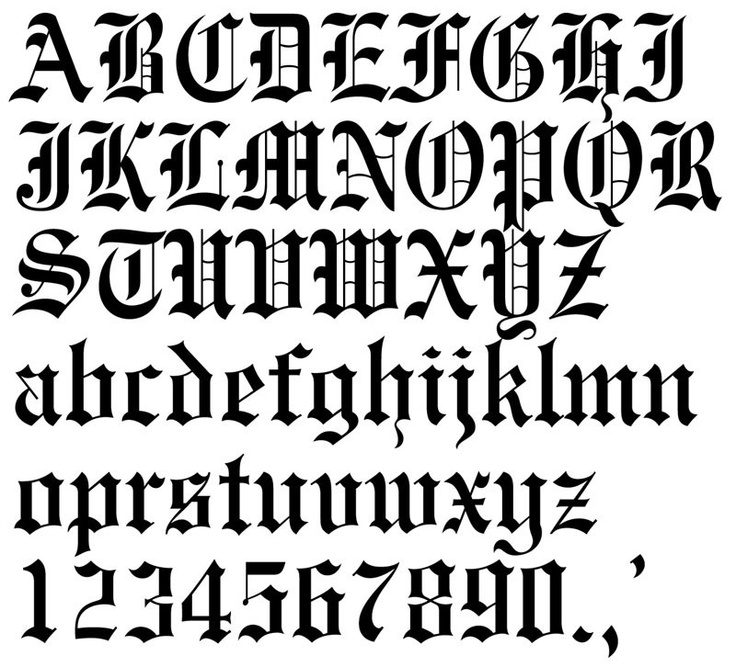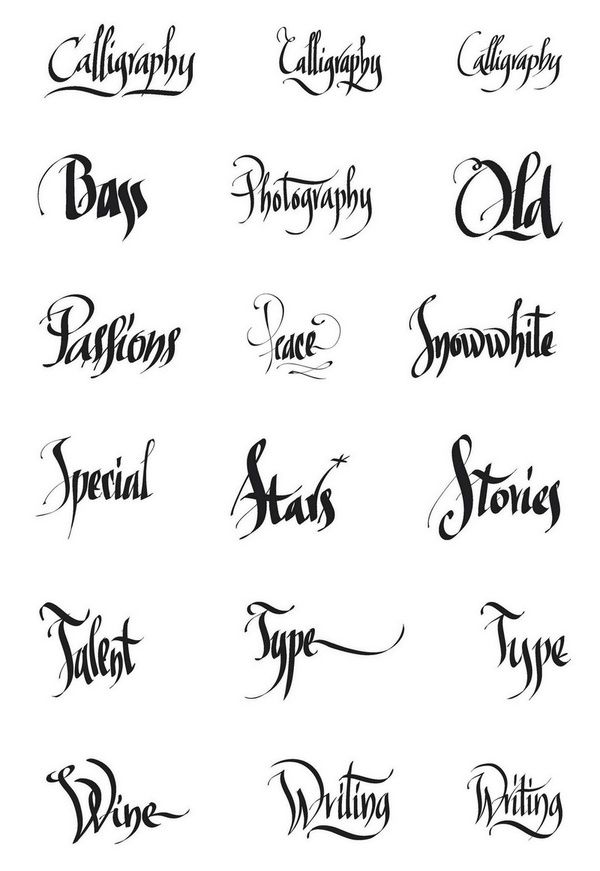
Тату надписи красивыми буквами. Подобрать шрифт для тату на латыни или латинские шрифты для тату надписей! Виды шрифтов для нанесения татуировок в виде надписей
Татуировки были популярны всегда. В древние времена они несли информацию о своем обладателе, его статусе и положении в обществе. Сегодня уже никто не судит о людях по надписям на их теле. Татуировки надписи стали еще одним способом самовыражения, который использует не только молодежь, но и люди постарше.
В качестве тату, что только не используют, разнообразные рисунки, абстракции и вязи непонятных символов, но особой любовью у молодежи пользуются тату надписи. Это наиболее яркий способ выразить себя, сказать миру и окружающим людям, о своих мыслях и предпочтениях, донести свой взгляд на вещи.
Татуировки все также многое говорят о своем обладателе. Но теперь уже – это информация о том, какого стиля жизни он придерживается, каким характером обладает.
Все чаще молодежь выбирает латинский шрифт для тату.
Это современно и модно, стильно и ярко. Да, и что говорить, ассортимент латинских шрифтов гораздо более широк, чем тех же русских.
Сегодня, когда в моде все иностранное – одежда, музыка, книги, неудивительно, что выбор подрастающего поколения падает именно на латинский шрифт для татуировок.
Этот важный вопрос предстоит решить перед тем, кто решил сделать татуировку, ведь хочется, чтобы надпись не только «говорила» о внутреннем мире, но и выглядела стильно и оригинально. У нас на сайте представлены все существующие шрифты для татуировок на латыни, начиная от древних и заканчивая современными. Готический шрифт или эмо, плавные линии и резкие углы, витиеватая вязь или строгие печатные буквы – найдется всё.
Тату надписи становятся более модными и популярными в наши дни. Их востребованность объясняется тем, что все больше людей по всему миру выбирают в качестве татуировки не простой рисунок, а текст с глубоким смыслом. Текстовые фразы могут представлять собой важные слова, имена, короткие цитаты или афоризмы, позволяющие продемонстрировать окружающим людям свои взгляды на жизнь. В статье подскажем, какой шрифт для тату можно выбрать парню или девушке, а также, рассмотрим красивые виды надписей в различных стилях.![]()
Как подобрать шрифт для тату?
Подбор шрифтов для тату – долгое и нелегкое занятие. Вообще, в интернете существует множество сайтов и программ, позволяющих подбирать шрифты для тату надписей online. Однако, если вы не хотите встретить другого человека с таким же красивым шрифтом, советуем вам обратиться к мастеру, который разработает стили тату надписей специально для вас. Конечно, за эту услугу придется доплатить, но в итоге, вы получите неповторимые красивые буквы, которые больше ни у кого не найдете.
В целом, девушкам больше приходятся по душе витиеватые, тонкие и изгибистые линии письма, которые часто украшаются дополнительными элементами: звездами, бабочками, цветами и пр. В то время как мужчины отдают свой выбор в пользу жирных, черных и толстых букв.
Отметим то, что отдельное внимание стоит уделить не столько внешнему виду надписи, сколько правильно подобранному интервалу между буквами. Ведь в том случае, если мастер нанесет маленькие буквы близко друг к другу, надпись со временем превратиться в нечитаемый партак, который нужно будет удалять лазером или перебивать каким-либо рисунком.
Виды шрифтов для тату
Вы хорошо подумали и решили, что хотите сделать тату надпись на своем теле. Следующий важный шаг, который необходимо совершить – это решить, какой тату шрифт вы бы хотели использовать для своего текста. Поскольку никто бы не хотел, чтобы татуировка выглядела скучно и непривлекательно, следует провести некоторое исследование и выбрать тот шрифт тату, который придаст вам больше красоты и индивидуальности.
Самые популярные шрифты для татуировки – это латинские, кельтские, английские и русские буквы. Именно они впечатляют большинство любителей боди-арта, поскольку выглядят индивидуально и уникально. Древнеанглийские шрифты также часто используются в татуировках, потому что они имеют утонченный вид и создают атмосферу средневековья. Другие красивые варианты стилей включают в себя граффити, каллиграфию, чикано, минимализм, готику, печатный алфавит и пр.
Латинский шрифт
Латинские буквы отличаются ясностью и геометрической простотой форм.